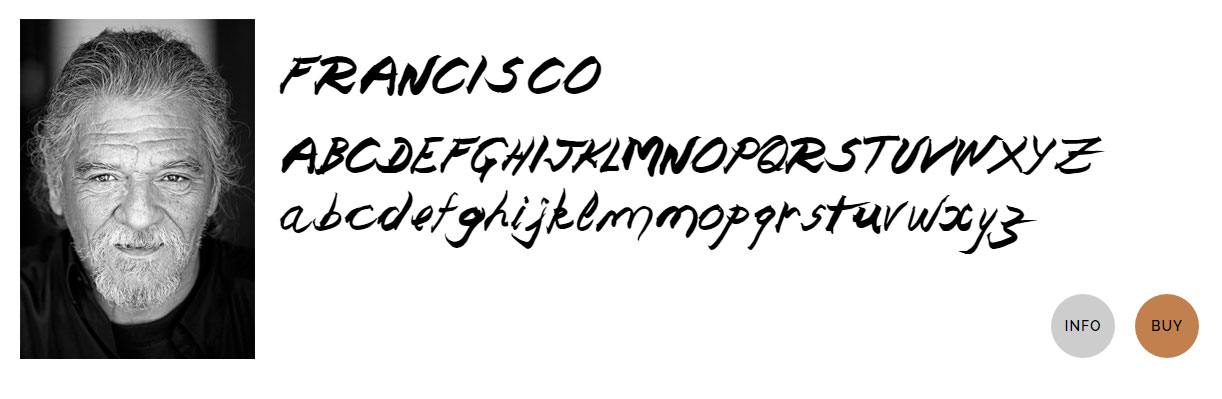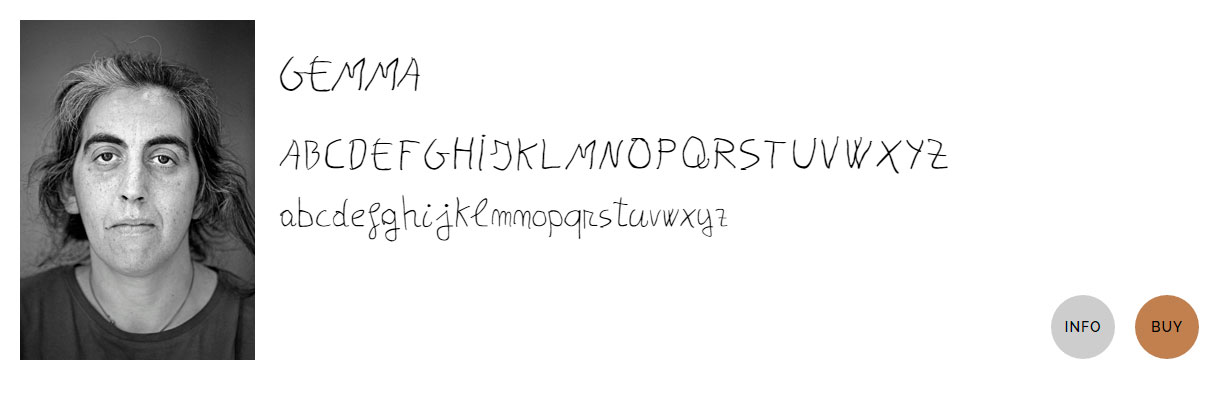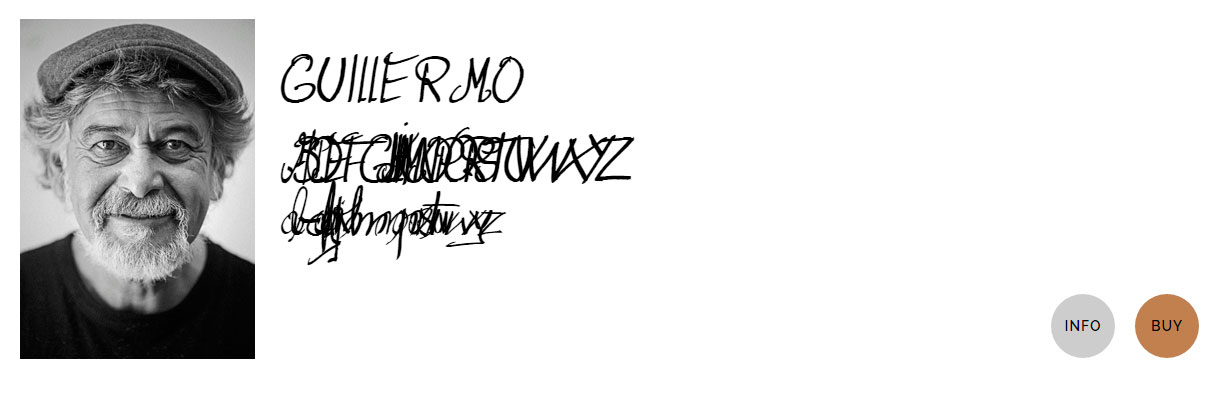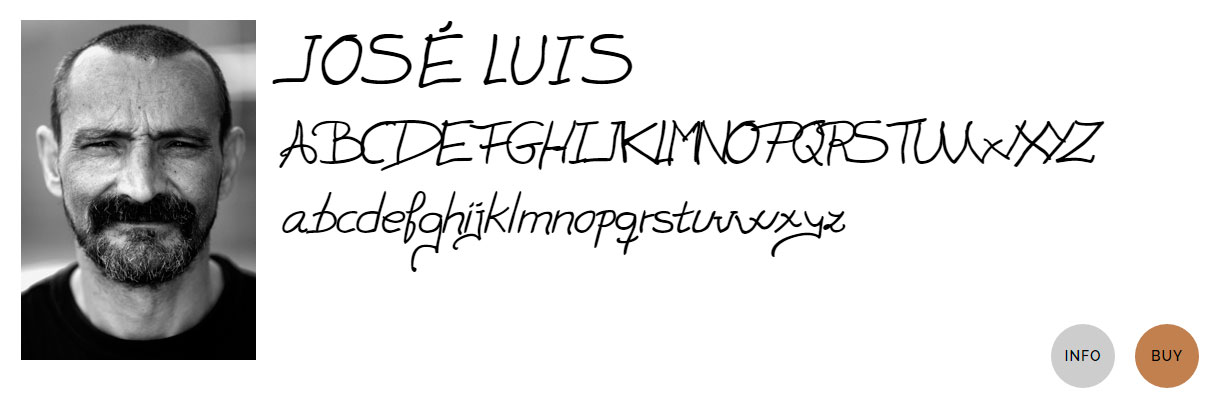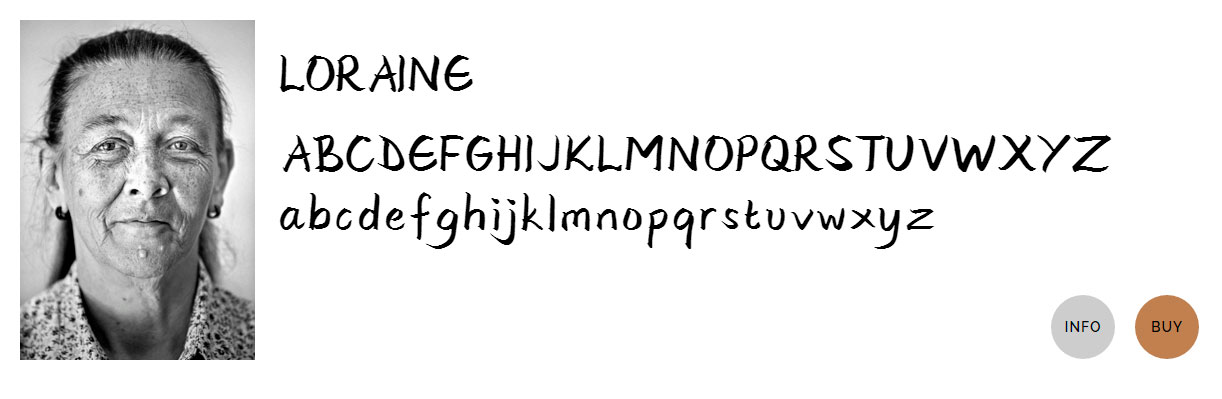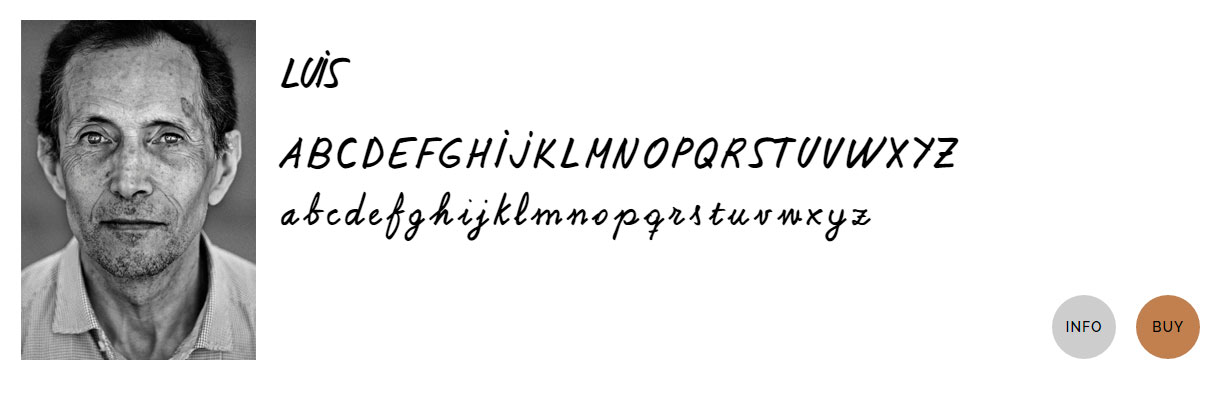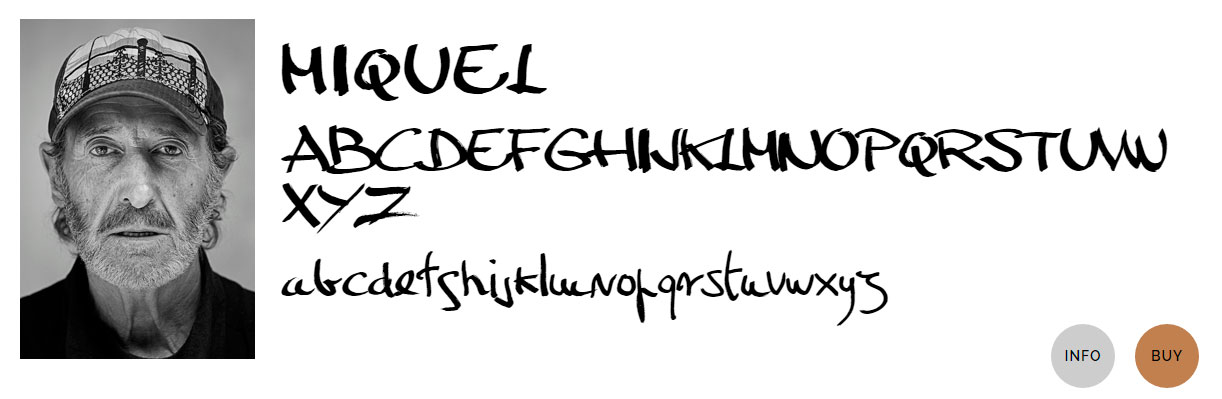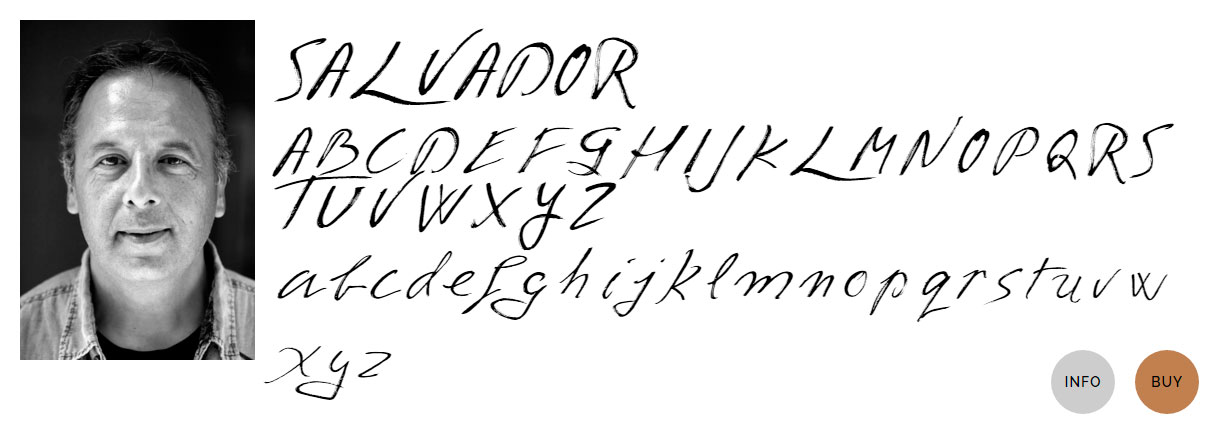
Projeto reúne tipografias criadas pelos sem-teto
Com a finalidade de ajudar os sem-teto da Espanha, a agência espanhola Cyranos McCann se uniu com a Fundação Arreals, de Barcelona, e lançaram um projeto chamado HOMELESSFONTS.
HOMELESSFONTS é uma iniciativa que viabiliza uma coleção de fontes para download, onde todas as tipografias foram desenvolvidas a partir da escrita à mão dos sem-teto que vivem nos arredores espanhóis – aquelas escritas que geralmente são vistas nos cartazes de papelão onde eles próprios escrevem suas necessidades, desabafos ou pedidos.
A ideia é que as fontes sejam utilizadas em projetos de comunicação visual e que todo o lucro, obtido com a compra das fontes, seja convertido em doações para a Fundação.
Para os designers, ou qualquer apaixonado por tipografias, é uma bela troca de solidariedade! ;)